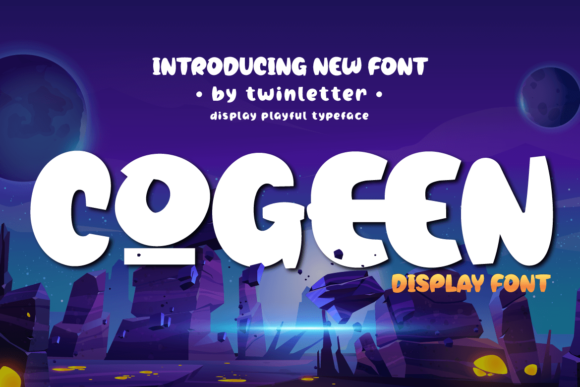
[Creativefabrica] Cogeen Font (2021)
Cogeen - это классный и игривый шрифт.
Независимо от темы, этот шрифт станет отличным дополнением к вашей библиотеке шрифтов, так как он способен приподнять любое творение.